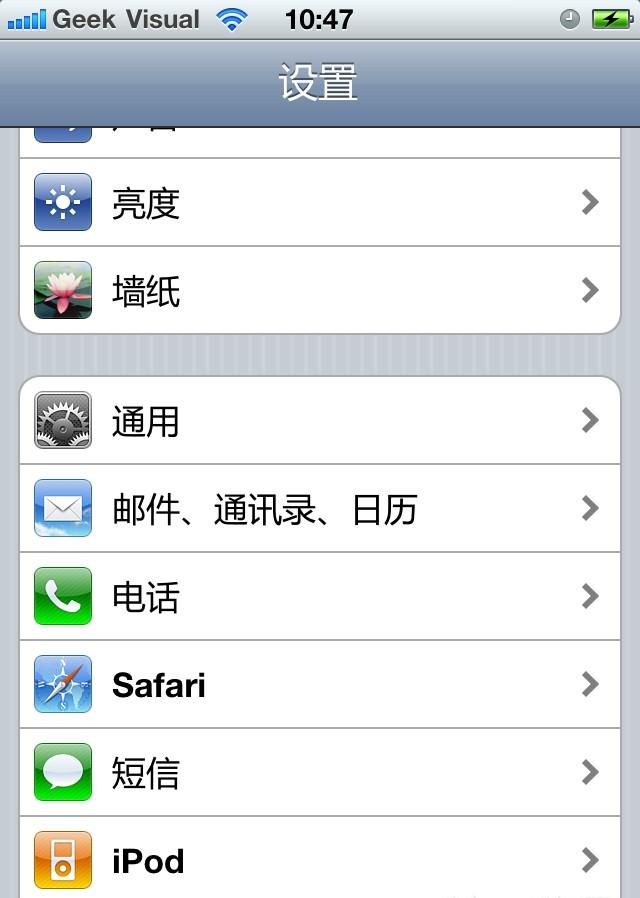
微軟雅黑是美國微軟公司委托中國北大方正電子有限公司設(shè)計(jì)的一款全面支持ClearType技術(shù)的字體。Monotype公司負(fù)責(zé)字體Hinting工作。它屬于OpenType類型,文件名是MSYH.TTF,字體設(shè)計(jì)上屬于無襯線字體和黑體。這種字體每個字的造價(jià)成本在100美元左右。該字體家族還包括“微軟雅黑Bold”(粗體),文件名為MSYHBD.TTF。這個粗體不是單純的將普通字符加粗,而是在具體筆畫上分別進(jìn)行處理,因此是獨(dú)立的一個字體。
顯示品質(zhì)優(yōu)異的斜體。
同樣是字體斜體處理,總體的斜體顯得有些支離破碎了,相較之下,雅黑字體的斜體的清晰度實(shí)在感人;
更清晰的小號字顯示。
得益于微軟方面下了血本進(jìn)行字體的單獨(dú)設(shè)計(jì),微軟雅黑字體的小號字顯示十分漂亮。以往, 12px 是宋體能顯示的極限。
單獨(dú)設(shè)計(jì)的粗體。
以往的宋體粗體都是通過內(nèi)嵌點(diǎn)陣或者字體引擎批量渲染的,效果一般;微軟雅黑字體選擇了單獨(dú)重新設(shè)計(jì),人力成本翻倍,效果自然也更好;
對于最常用的字號。
即使是小子號也能完美顯示的雅黑字體,用戶中英文搭配也十分和諧;且同樣的字號,微軟雅黑字體相較其他的字號偏大,更易識別,閱讀起來也更舒服;
更優(yōu)美而現(xiàn)代的字形設(shè)計(jì)。
對于設(shè)計(jì)師而言,微軟雅黑字體的出現(xiàn)給他們帶來了很大方便。在進(jìn)行網(wǎng)頁設(shè)計(jì)或者其他平面設(shè)計(jì)時(shí),只需要直接輸入就可以創(chuàng)建出很漂亮的版面設(shè)計(jì)效果了